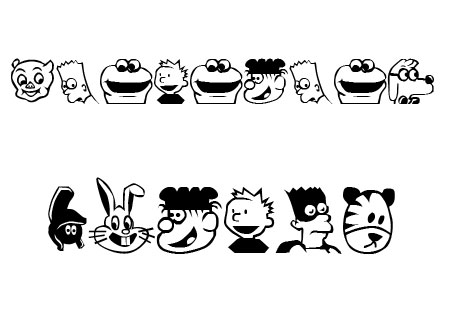
Интересная задумка)
Как сделать эти символы
Тут даже Кевин и Хобс есть :DDD
Да, таким ничего не напишешь, но вид создает красивый))
На шрифт не очень похоже но мне нравится=)Супер
Кульненько!!!